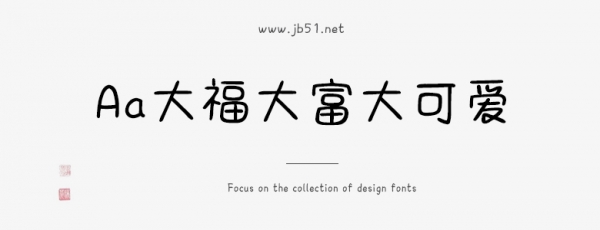
Aa大福大富大可愛(ài)是一款不錯(cuò)的藝術(shù)字體,由Aa字庫(kù)出品,字體筆觸適中,書(shū)寫(xiě)流暢,字形圓潤(rùn),具有很好的視覺(jué)感,適合應(yīng)用于藝術(shù)設(shè)計(jì)、平面宣傳設(shè)計(jì)、網(wǎng)頁(yè)設(shè)計(jì),書(shū)法字帖等領(lǐng)域,需要的朋友可以前來(lái)本站下載。